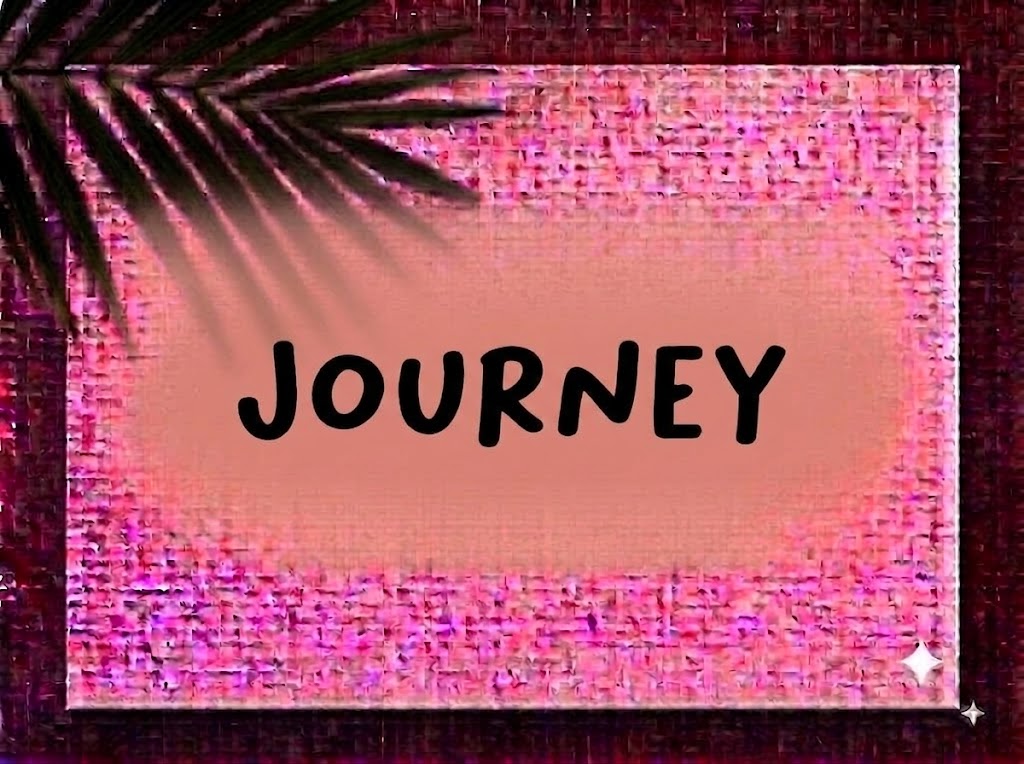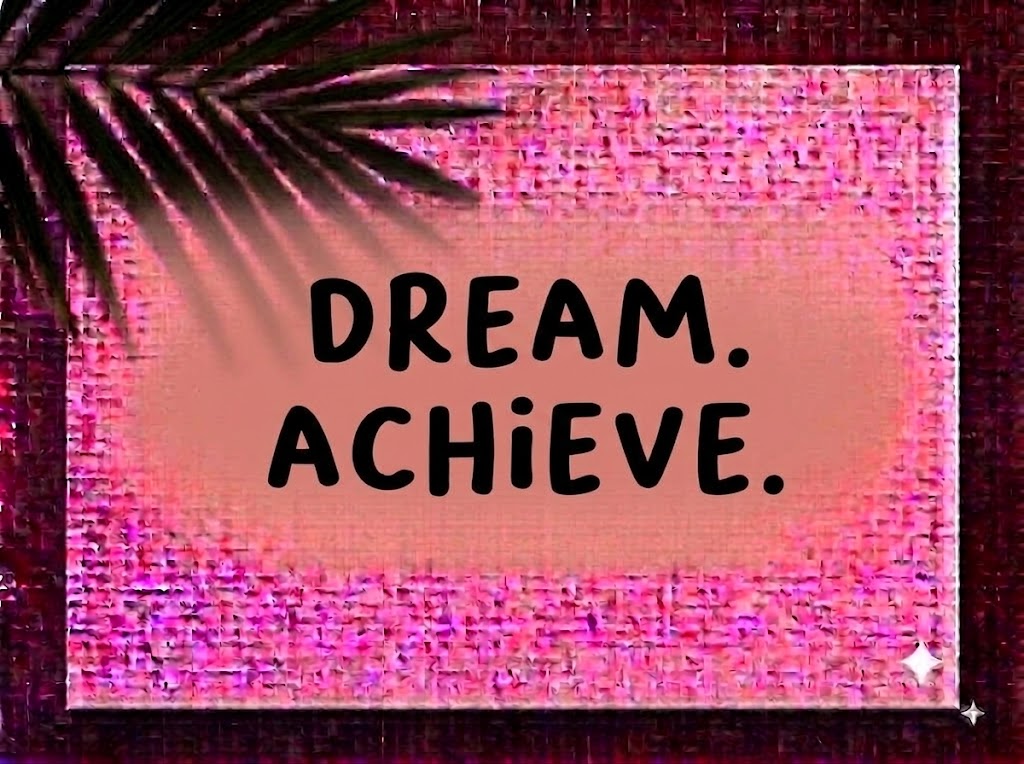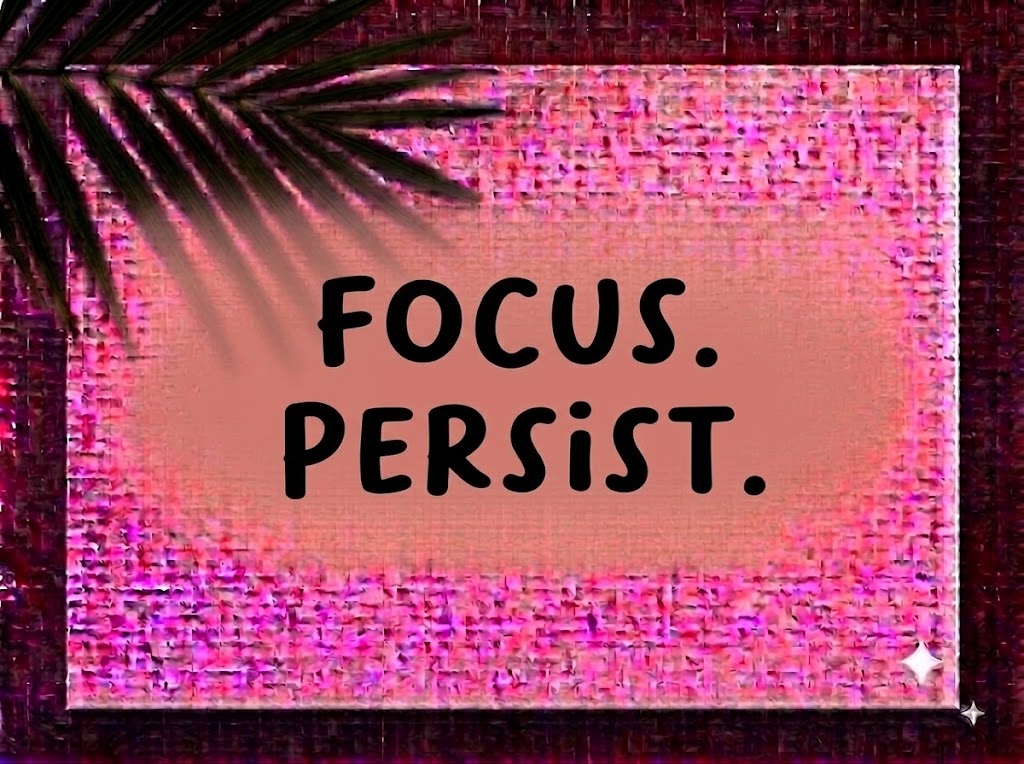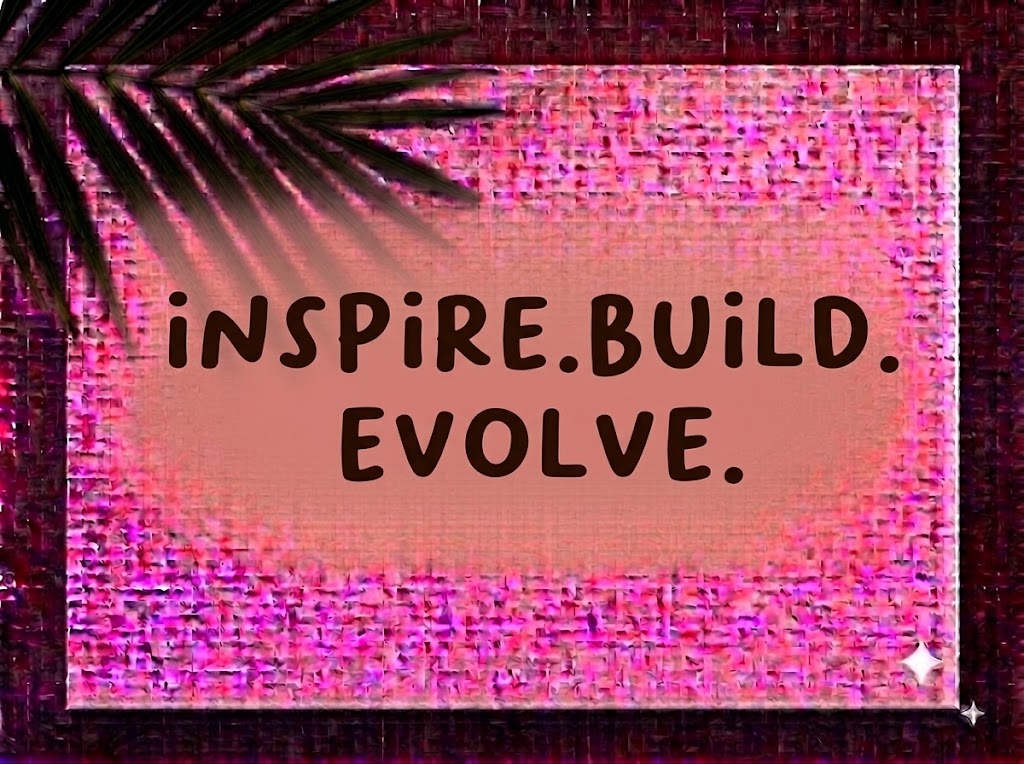
Trong sáng tạo nội dung số và thiết kế truyền thông giải trí, những bộ phông chữ mang phong cách vẽ tay bút dạ (Hand-drawn Comic Marker) với nét chữ mập mạp, tinh nghịch luôn tạo nên sự lôi cuốn đặc biệt. Đường nét tự do, mềm mại và tròn trịa không chỉ mang lại cảm giác thân thiện, tươi vui mà còn giúp thông điệp trở nên gần gũi, kích thích thị giác mạnh mẽ ngay từ ánh nhìn đầu tiên.
Nếu bạn đang tìm kiếm một phông chữ hiển thị ngộ nghĩnh, đậm chất truyện tranh để làm video ẩm thực đường phố, thiết kế ảnh bìa thumbnail YouTube, bao bì đồ ăn vặt hay biển hiệu quán trà sữa, font 1FTV VIP Bakso Sapi chính là sự lựa chọn không thể bỏ qua.
Giới thiệu về font 1FTV VIP Bakso Sapi
Font 1FTV VIP Bakso Sapi là bộ chữ hiển thị trang trí (display font) lấy cảm hứng từ những nét vẽ tay ngẫu hứng bằng bút lông dạ bảng và bảng hiệu đường phố dân dã:
Tên phông chữ: 1FTV VIP Bakso Sapi
Đặc điểm nổi bật của ngôn ngữ thiết kế VIP Bakso Sapi
Sức hút thị giác của font 1FTV VIP Bakso Sapi đến từ phom dáng đầy đặn cùng tinh thần truyện tranh tươi trẻ:
Nét chữ mập mạp, ấm áp (Chubby Marker Strokes): Trọng lượng nét dày dặn, các góc cạnh được bo tròn mềm mại mô phỏng nét mực bút dạ đậm màu, tạo cảm giác no tròn, thích mắt như chính tên gọi món ăn đường phố quen thuộc.
Tạo hình bất quy tắc ngẫu hứng: Điểm nhấn đắt giá nằm ở nhịp điệu chữ không quá gò bó theo khuôn thước máy móc. Các nét cong uốn lượn nhẹ nhàng ở các chữ cái như
B,K,R,S,G,Q,Otạo cảm giác sinh động, vui vẻ và tự nhiên như chữ viết tay thực tế.
Tối ưu hiển thị và dấu tiếng Việt từ 1FTV
Để phông chữ vận hành mượt mà trên cả hai hệ điều hành Windows và macOS, phiên bản này đã được xử lý kỹ lưỡng về mặt thông số nội tại:
Khoảng cách ký tự (Kerning): Khoảng hở giữa các chữ cái được tinh chỉnh hợp lý, giúp các nét chữ to bản khi đứng cạnh nhau không bị dính nét hay gây cảm giác ngột ngạt cho người xem.
Bản Việt hóa chuẩn chỉnh: Hệ thống dấu thanh tiếng Việt (sắc, huyền, hỏi, ngã, nặng, mũ, móc) được thiết kế đồng điệu theo phong cách tròn mập của thân chữ.
Hệ thống ký tự đồng bộ: Tích hợp trọn vẹn dãy số từ 0-9 phom dáng ngộ nghĩnh cùng đầy đủ các ký hiệu toán học và dấu câu cơ bản.
Đánh giá hiển thị thực tế
Khả năng hiển thị của phông chữ được tối ưu linh hoạt theo nhiều kích cỡ:
Kích thước nhỏ (12pt – 24pt): Nhờ độ dày nét đồng đều, các câu ngắn và dãy số vẫn hiển thị rõ ràng, dễ nhận diện trên màn hình điện thoại di động.
Kích thước lớn (36pt – 72pt): Đây là đất diễn lý tưởng nhất để 1FTV VIP Bakso Sapi phô diễn toàn bộ sự mũm mĩm.
Ứng dụng trong thiết kế đồ họa và sản xuất video
Sở hữu nét tính cách tươi vui và giàu năng lượng, font 1FTV VIP Bakso Sapi mở ra không gian ứng dụng phong phú:
Video ngắn (TikTok, Reels, Shorts): Dáng chữ comic hiển thị cực kỳ bắt mắt trên khung hình đứng tỷ lệ 9:16. Cực kỳ ăn nhập với các video mukbang
Ảnh thu nhỏ YouTube (Thumbnail): Lựa chọn hàng đầu cho các kênh Gaming vui nhộn, Food Review, Khám phá đời sống, Hoạt hình hay nội dung Thiếu nhi nhờ khả năng giật tít thu hút người xem tức thì.
Ẩm thực & F&B (Fast Food, Ăn vặt, Quán Café): Hoàn hảo để thiết kế menu quán trà sữa, bảng hiệu xe ăn vặt lưu động, nhãn dán hộp cơm, bao bì bánh kẹo, đồ hộp hay poster khuyến mãi món mới.